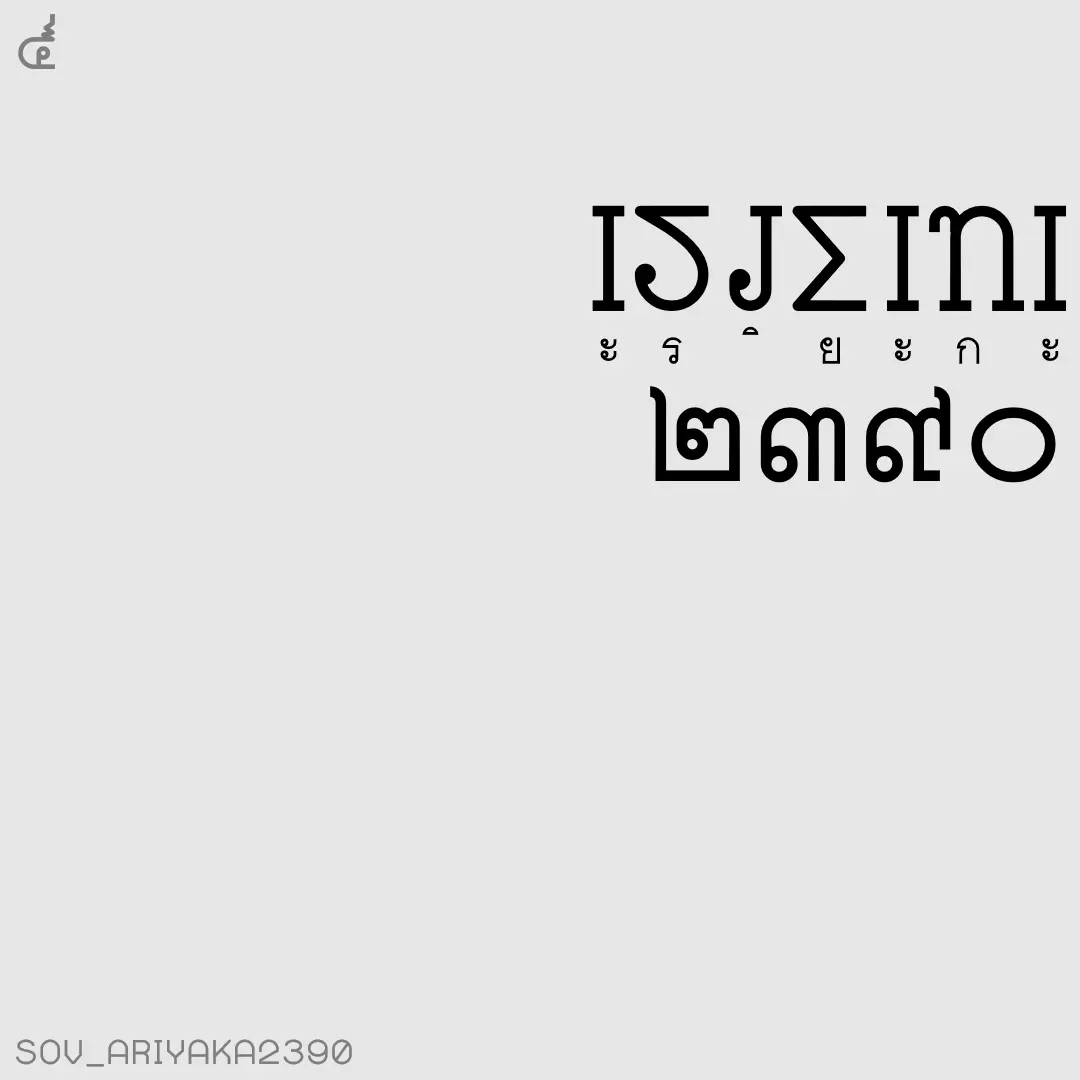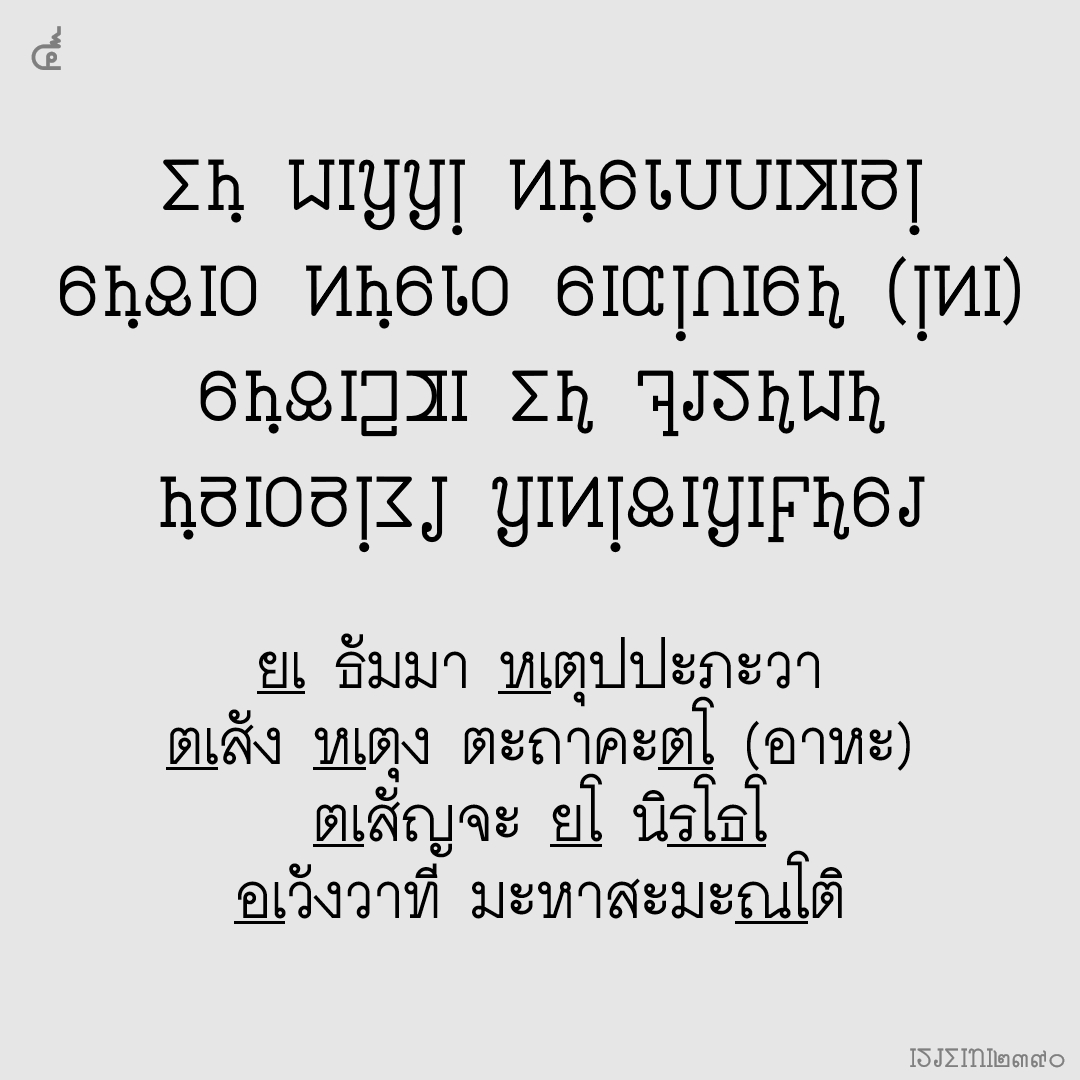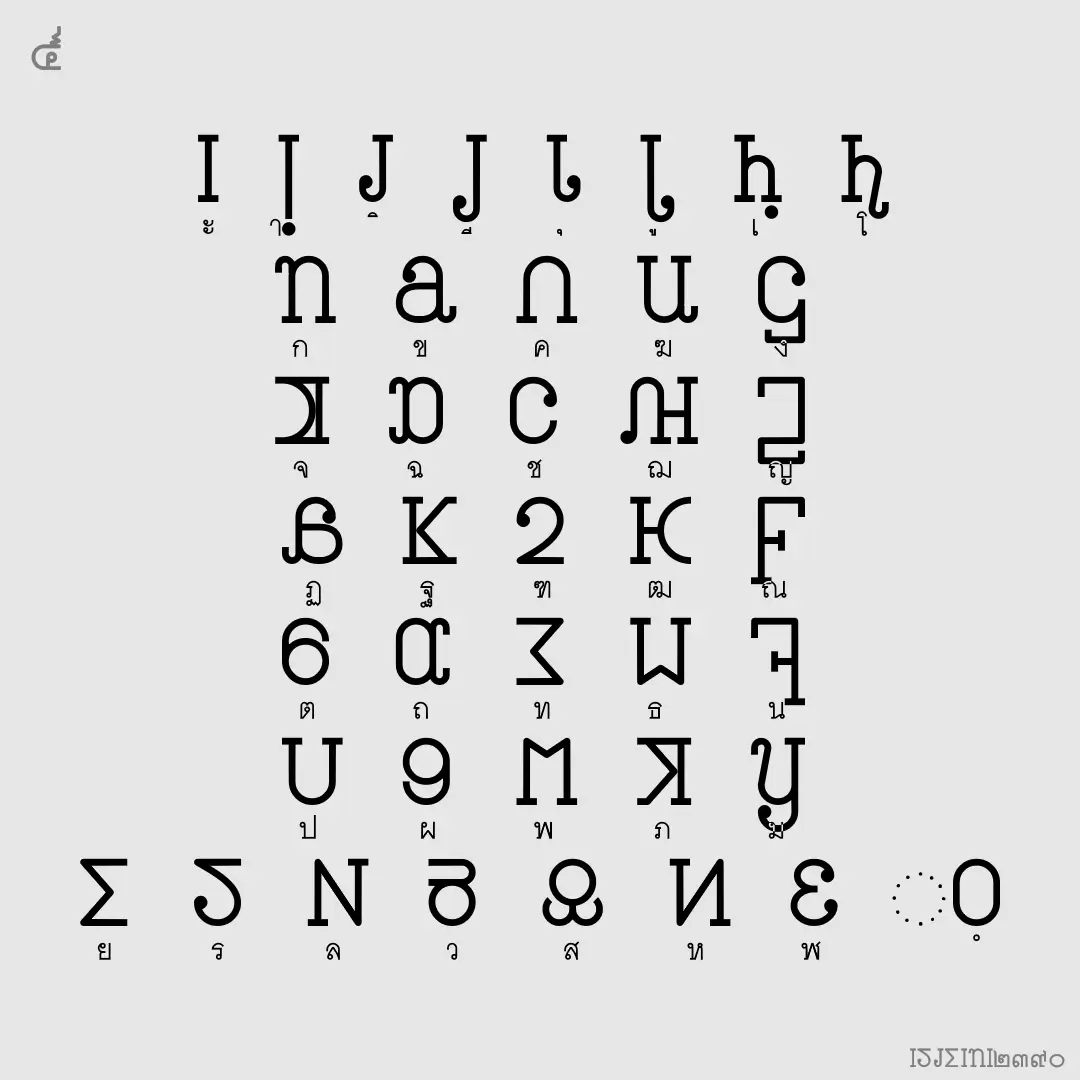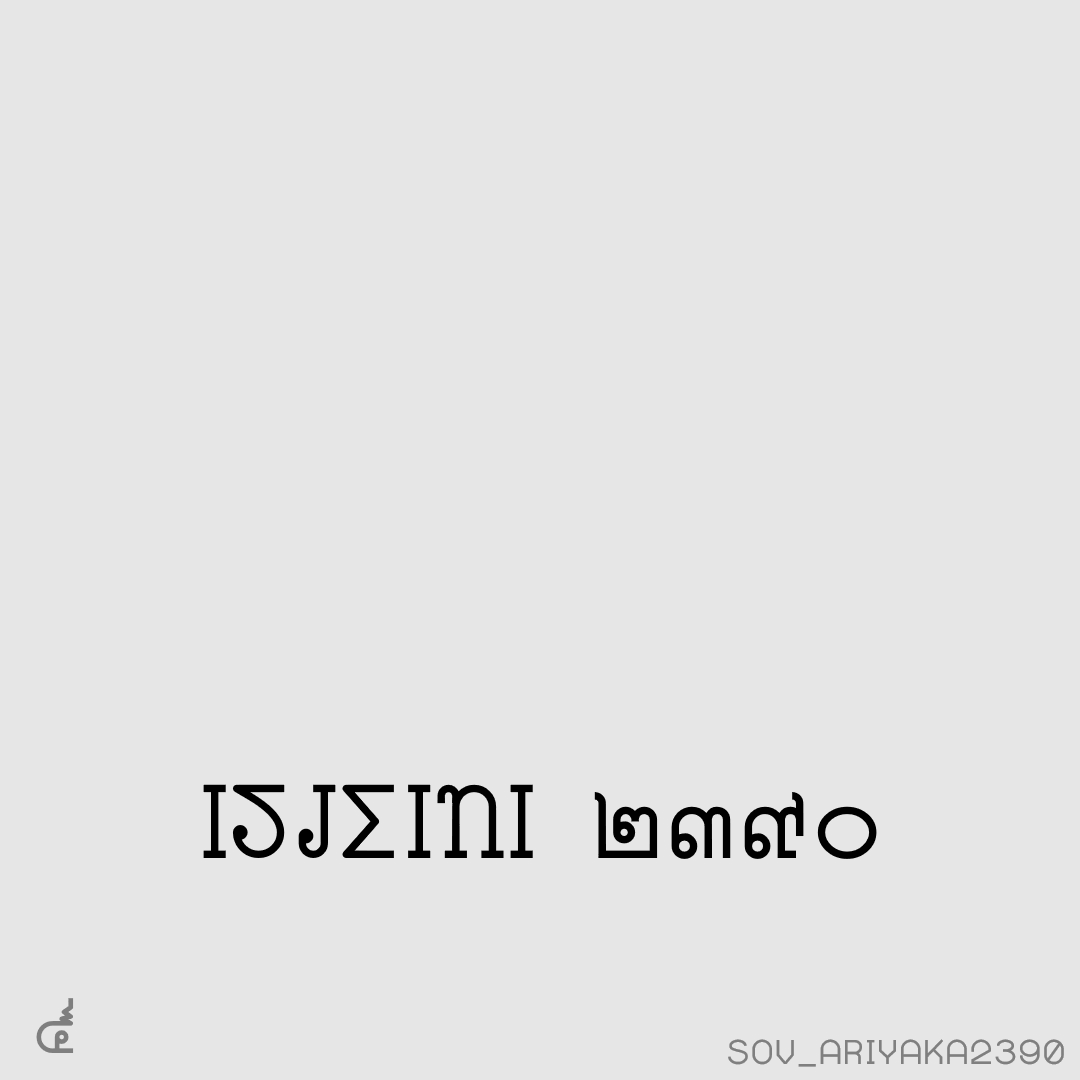
อริยกะ๒๓๙๐ (SOV_Ariyaka2390)
ทดลองทำฟอนต์อริยกะ ตัวพิมพ์ สำหรับภาษาบาลีเท่านั้น… วิธีพิมพ์เหมือนพิมพ์ตัวสะกด แต่สระจะต้องตามหลังพยัญชนะเสมอ (ไม่มีสระหน้า เช่น เ โ ก็ต้องพิมพ์ตามพยัญชนะ)
ฟอนต์ตัวปรกติ มีเฉลยใต้บรรทัด ถ้าชำนาญแล้ว ใช้ฟอนต์ตัวหนา
ปล. แถม ฟอนต์อริยกะพินทุ สำหรับคนเคยพิมพ์อักษรไทยพินทุอยู่แล้ว เอาไปเปลี่ยนฟอนต์ได้เลย ไม่ต้องพิมพ์ใหม่
เบื้องหลังการออกแบบ : ฟอนต์ อริยกะ๒๓๙๐